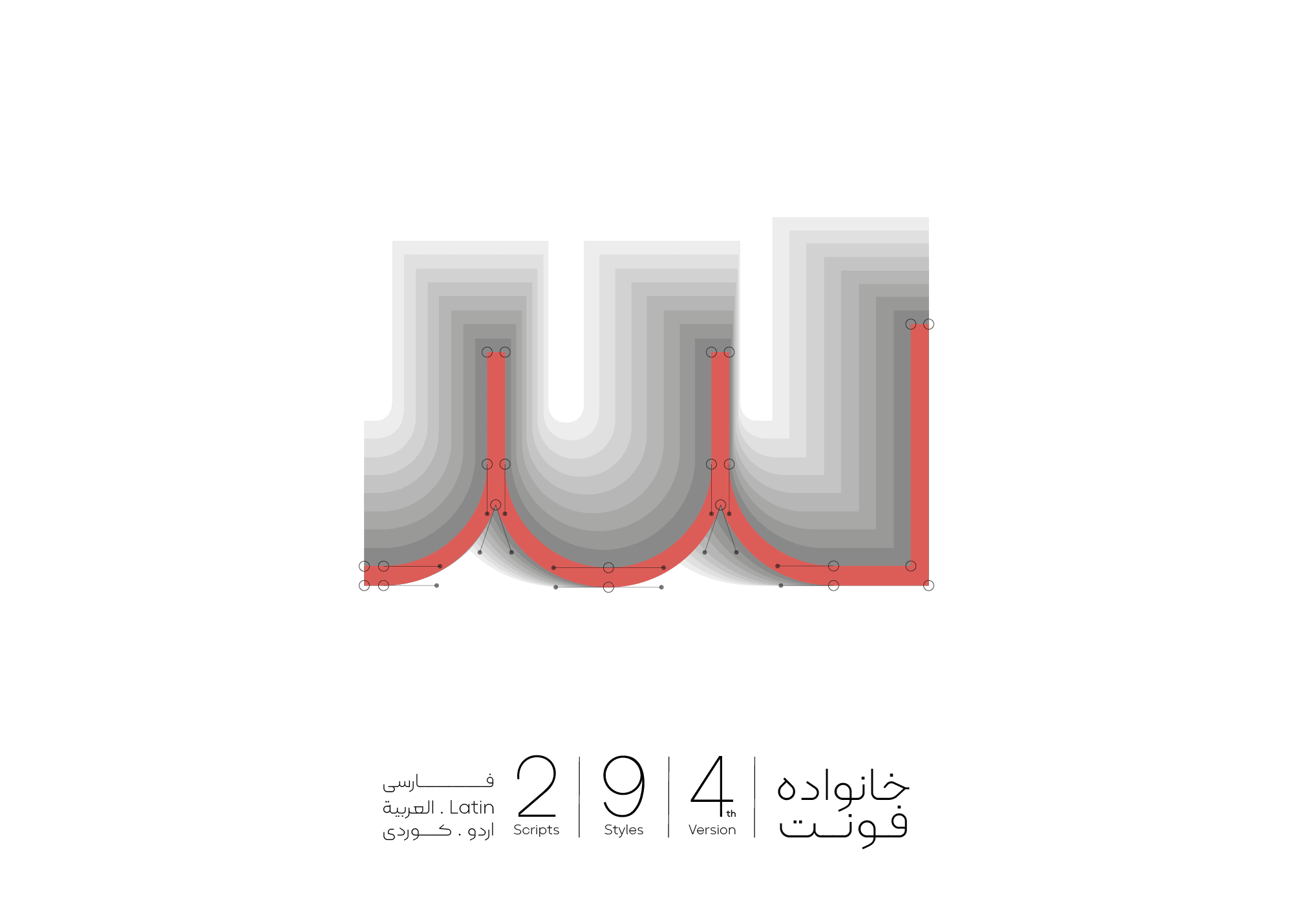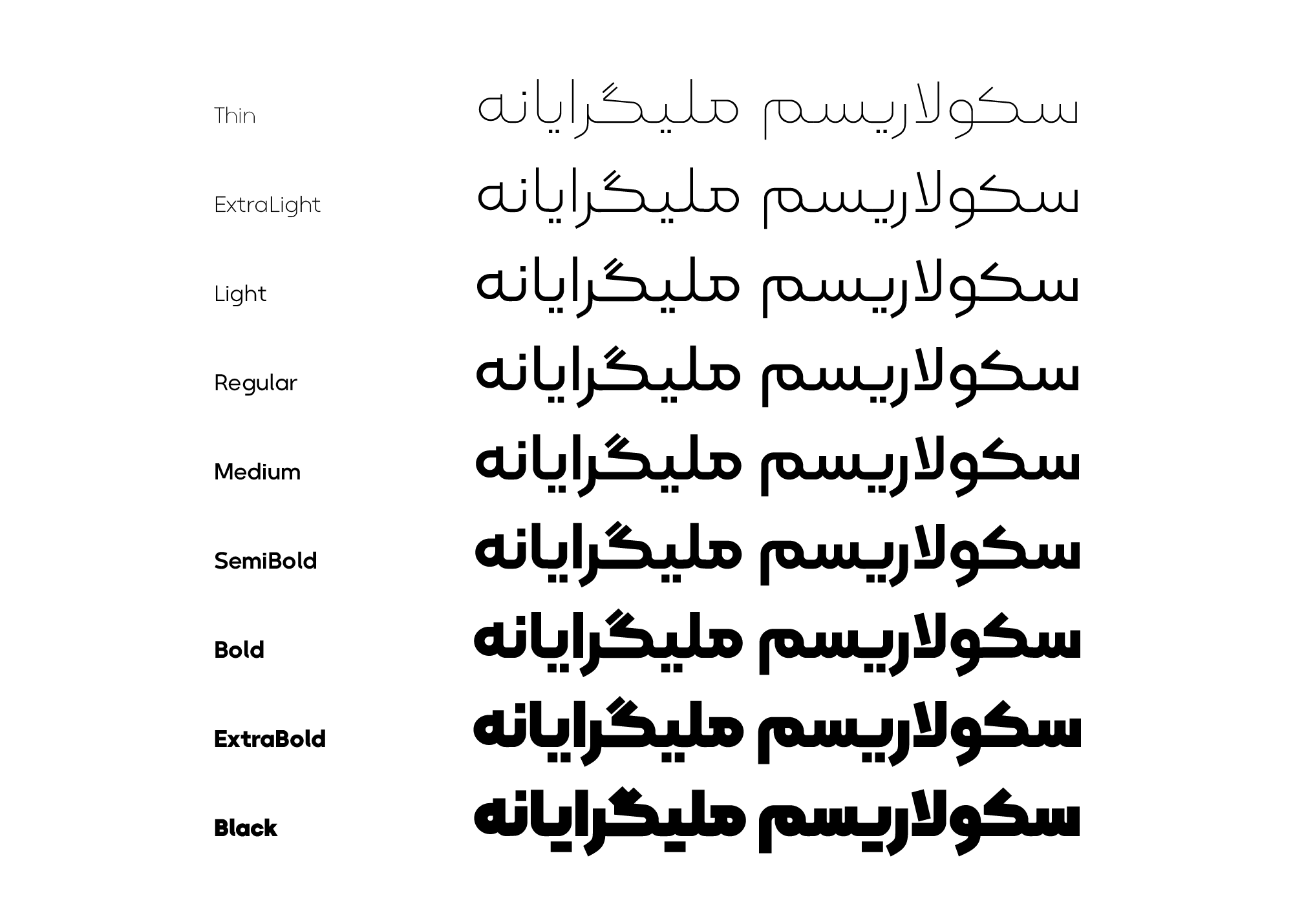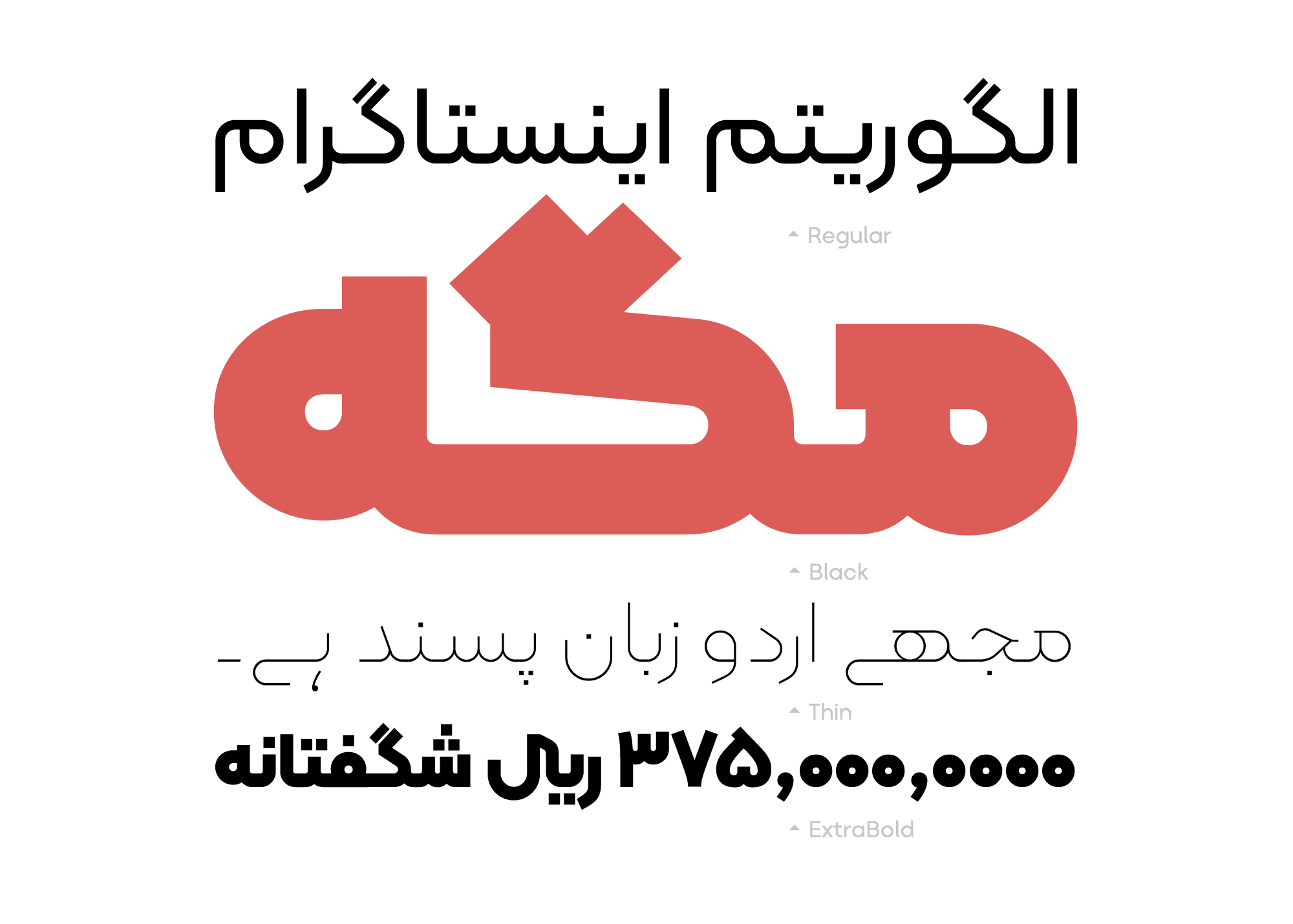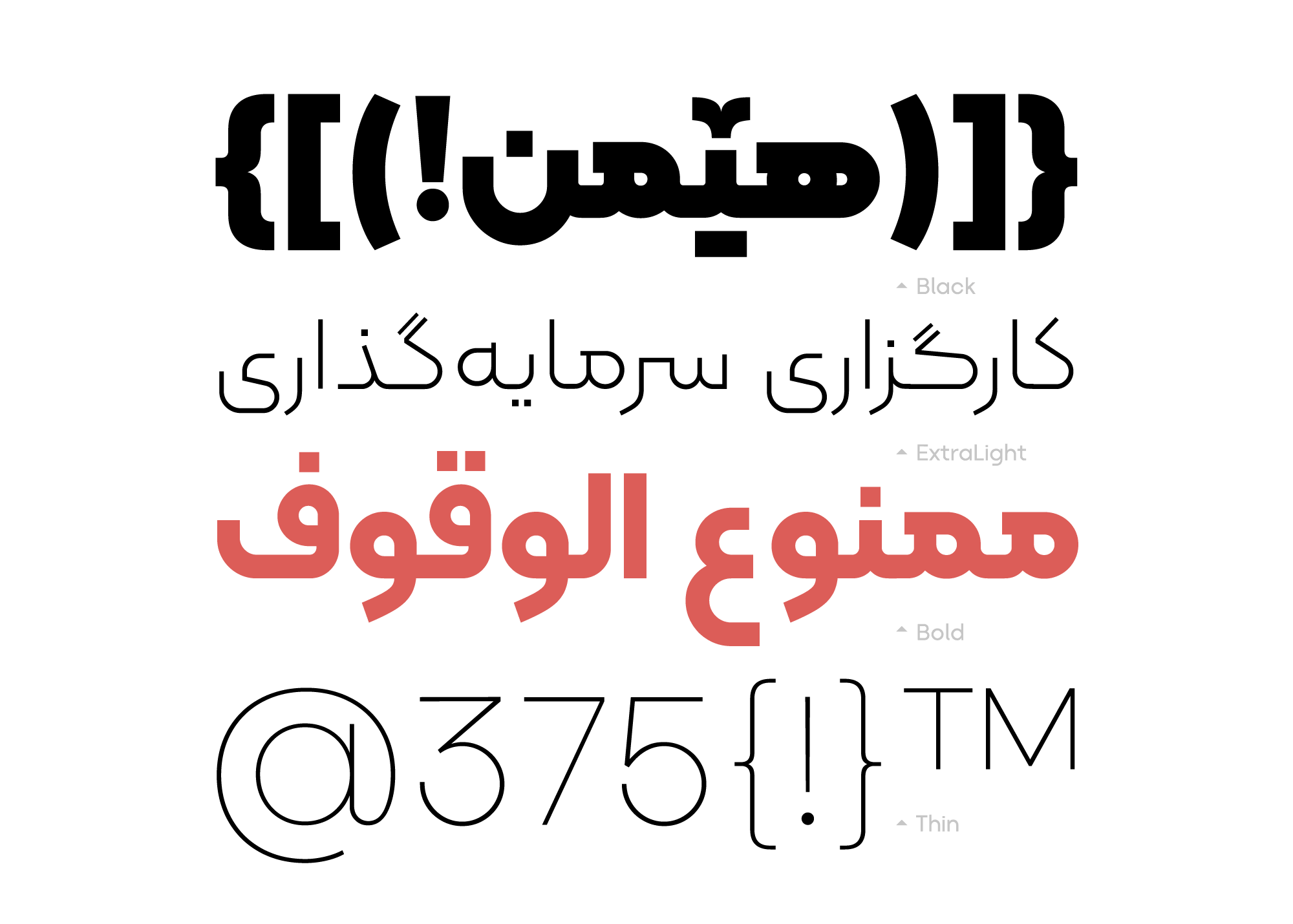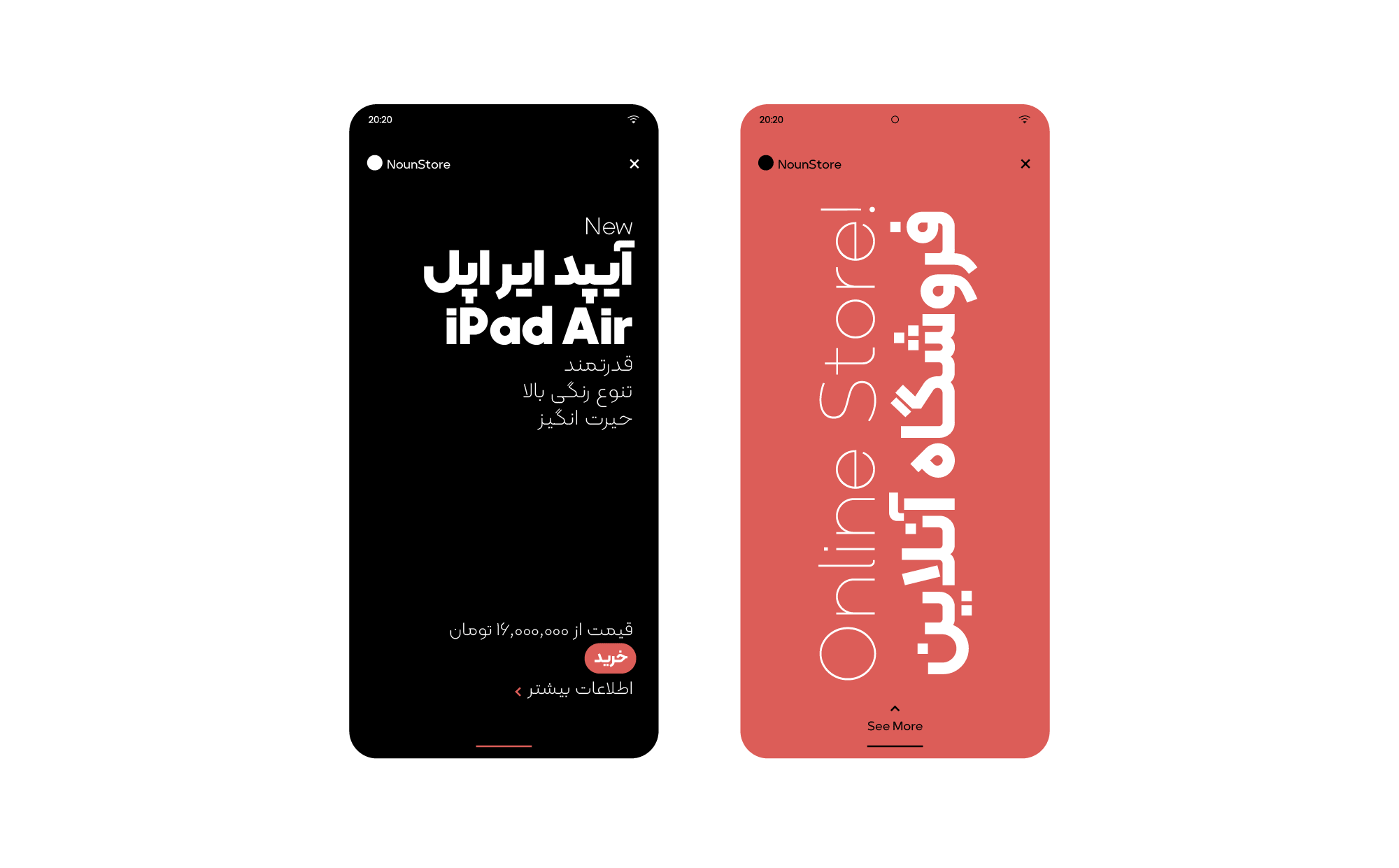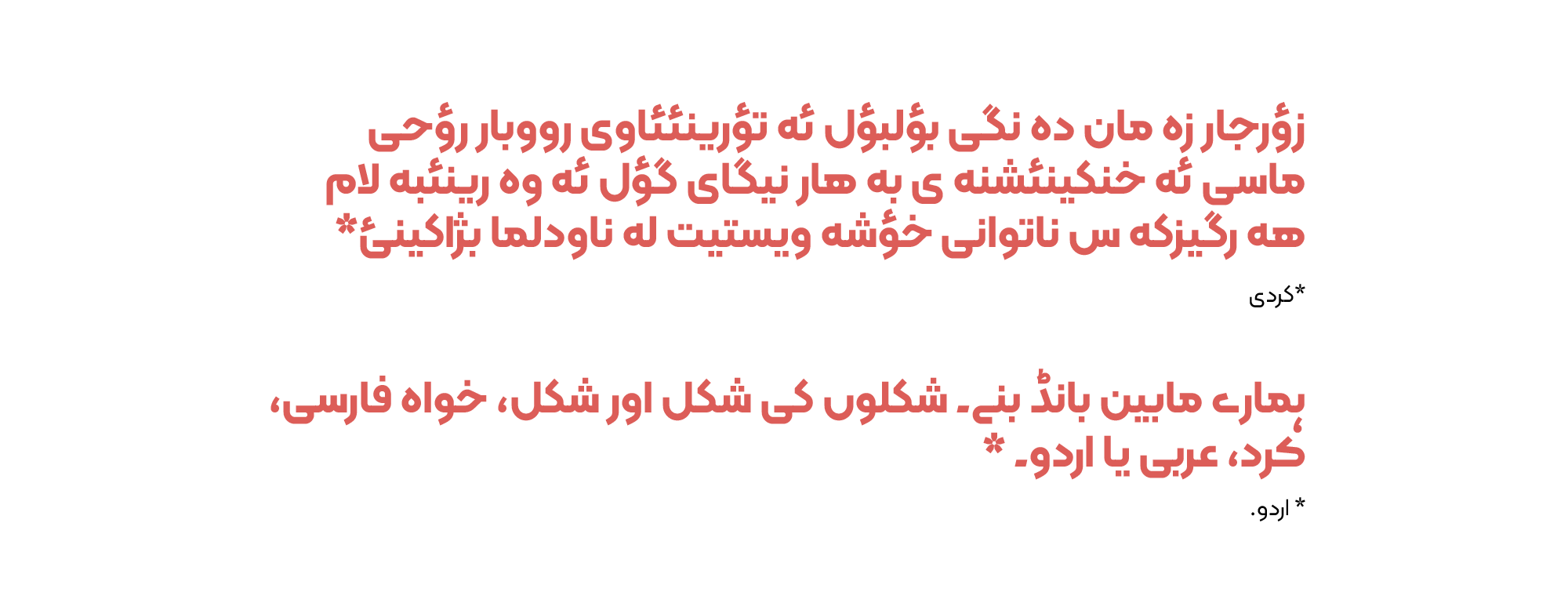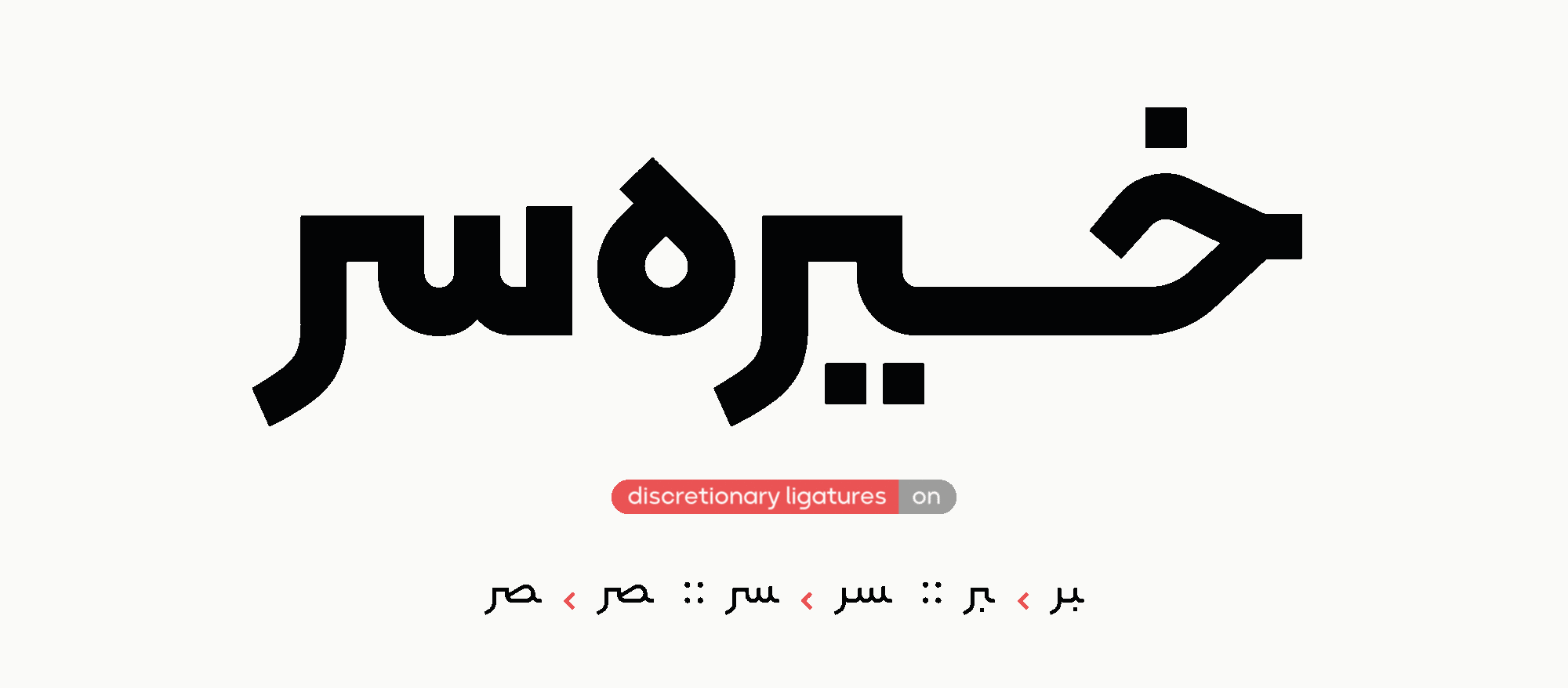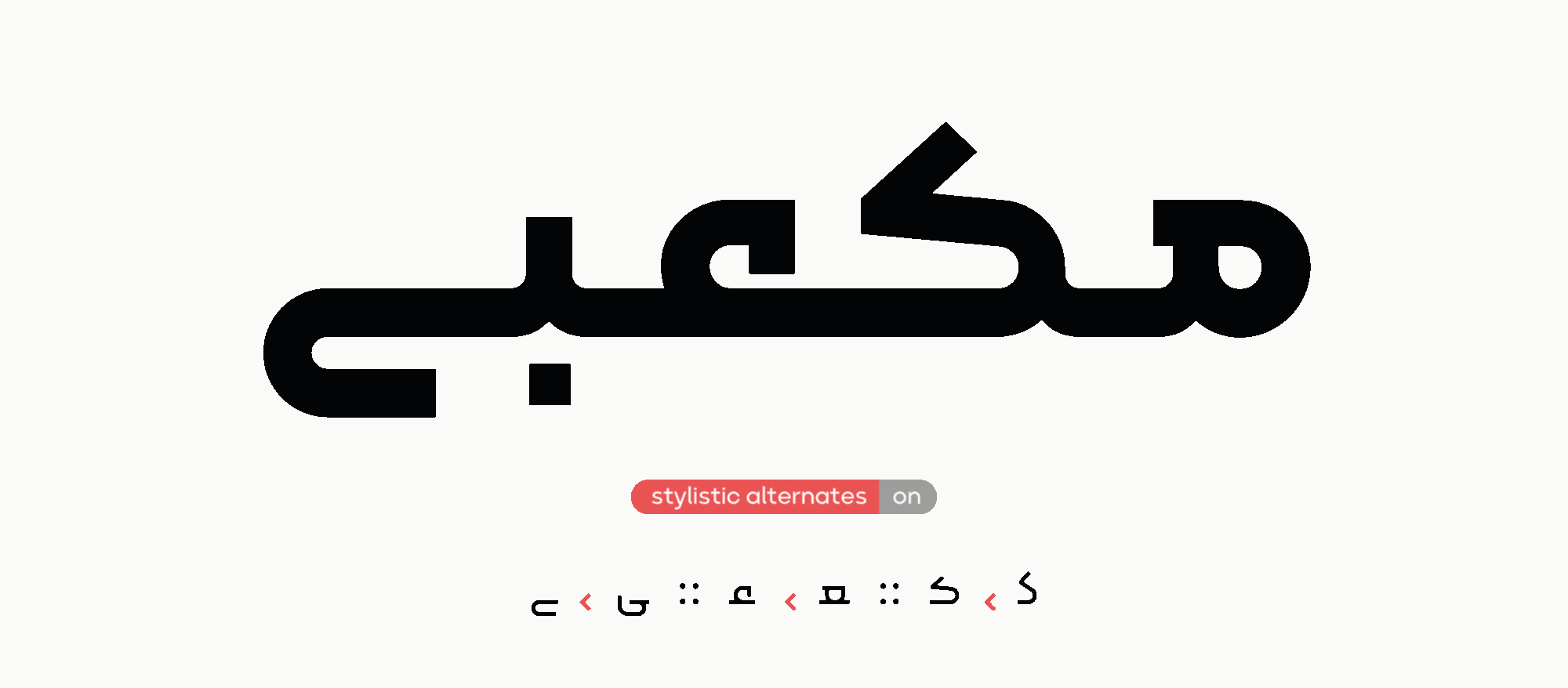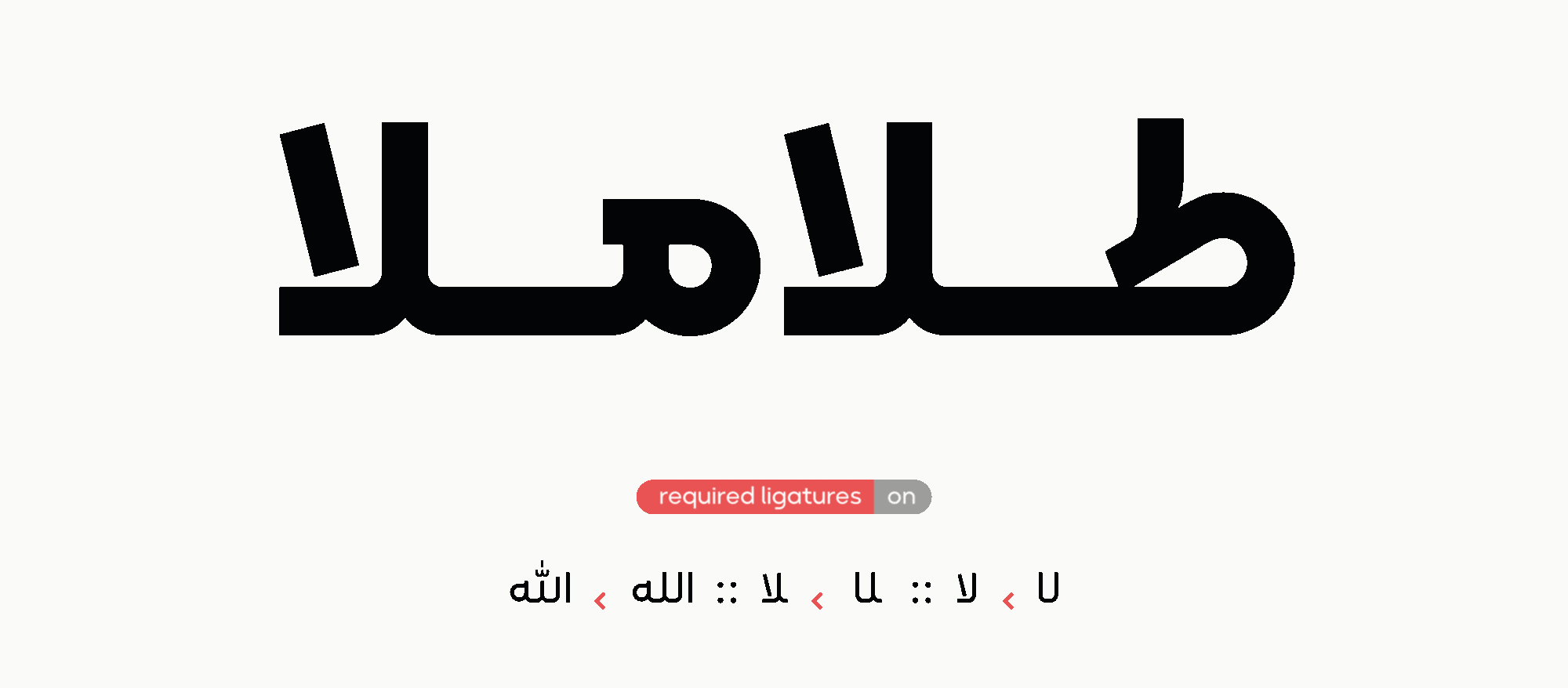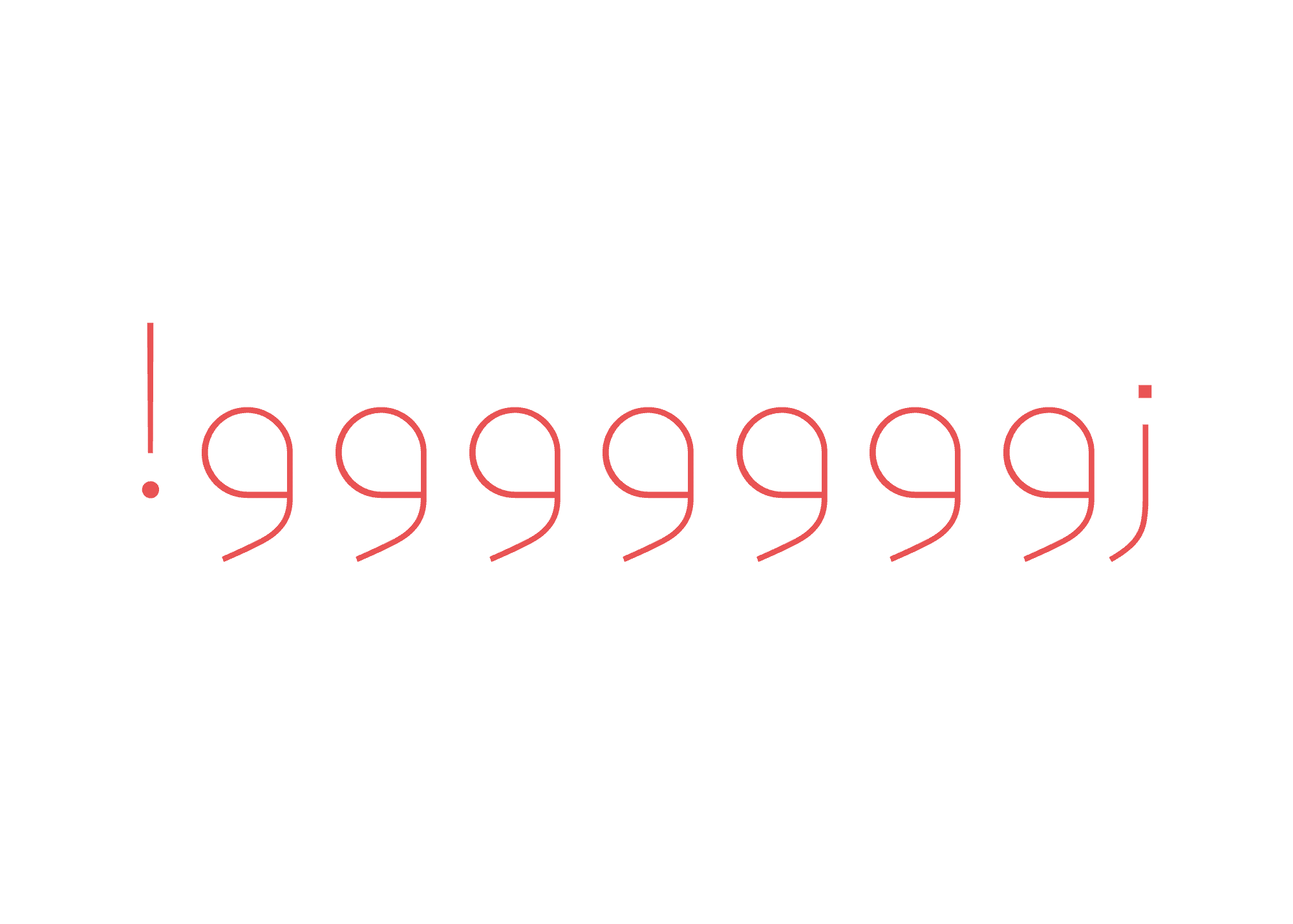
تنوع وزن
فونت کلمه یک خانواده کامل است که ۹ وزن دارد. از خیلی نازک تا سیاه تنوع کاملی از ضخامت و تیرگی را در اختیار شما قرار میدهد.
کاراکترهای انگلیسی
بهدلیل هماهنگی با حروفِ فارسی، کاراکترهای زبان انگلیسی نیز هماهنگ با حروف فارسی برای فونت کلمه طراحی شده است.
ترکیبات اختیاری Discretionary Ligatures
در فونت کلمه تعدادی ترکیبات جایگزین اختیاری وجود دارد که میتوانید به صورت دستی این ترکیبات اختیاری را در نرمافزارهای گرافیکی فعال کنید( برای آشنایی با شیوه فعالسازی میتوانید فایل راهنما در بسته فونت کلمه را مشاهده کنید).
Stylistic set حروف جایگزین اختیاری
در فونت کلمه میتوانید با فعالسازی Stylistic set از جایگزینهایی برای حرف «ک»، «ـع» و «ـی» بهره ببرید. در صورت تمایل میتوانید به صورت دستی این حروف جایگزین اختیاری را در نرمافزارهای گرافیکی فعال کنید ( برای آشنایی با شیوه فعالسازی میتوانید فایل راهنما در بسته فونت کلمه را مشاهده کنید).
required ligatures ترکیبات جایگزین الزامی
در فونت کلمه، برای اتصالات «لا» و نیز عبارت مقدس «الله» جایگزینهای مناسب طراحی و به صورت پیش فرض فعال درنظر گرفته شده است.